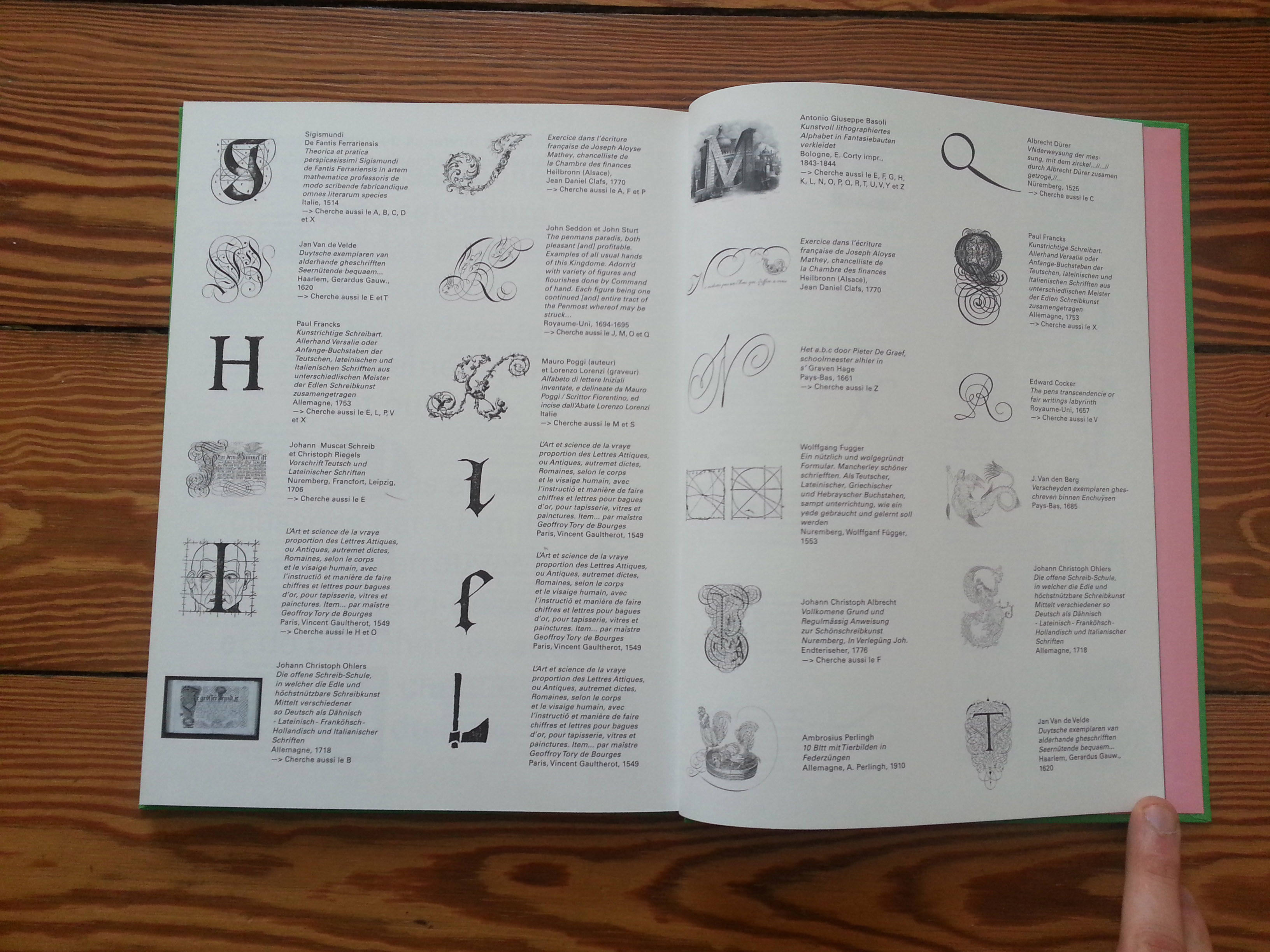
Si, si, bien sûr, tous les alphabets présents dans le livre sont listés avec toutes les références disponibles (certains alphabets ne sont pas attribués). Ceci étant, l'objet de ce livre-là est d'abord une déambulation graphique et non une étude sur ce fonds, cela faisait partie des demandes.
>Les photos que vous montrez ne permettent pas de voir si vous donnez bien les origines des illustrations (par exemple Q extrait de untel, tellivre…), c’est-à-dire si votre ouvrage est purement graphique ou un peu bibliologique voire typographique.
> En septembre dernier, la ville de Strasbourg a commandité un livre autour du fonds Soennecken. L'axe choisi pour cet ouvrage a été la lettre dessinée, et Guillaume Dégé a sélectionné dans le fonds un ensemble de lettres où le dessin prend en quelques sortes le pas sur la fonction (plusieurs alphabets de Midolle, Basoli, pour les plus connus). Autour des lettres issues du fonds patrimonial, 10 illustrateurs et graphistes contemporains ont été sollicités pour créer des alphabets avec cette même idée.